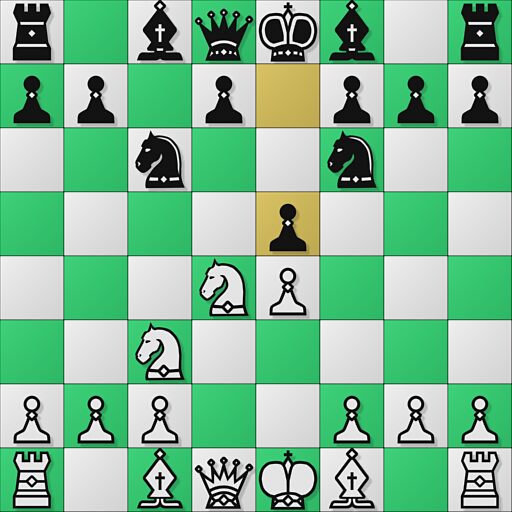
Chess 7 to darmowy font z szachowymi symbolami, utrzymany w prostym stylu gier planszowych. Symbole te wyglądają jak czytelne motywy szachowe, a nie ozdobne ikonki. Dzięki znanym sylwetkom figur i prostym geometrycznym kształtom zestaw jest bezpośredni i nie pozostawia wątpliwości co do swojej tematyki.
Świetnie sprawdzi się na ulotkach klubowych, plakatach turniejowych, kartach wyników, stronach z zadaniami oraz na opakowaniach gier – wszędzie tam, gdzie darmowy font z szachową grafiką sprawdzi się lepiej niż zwykły zbiór symboli. Użyj go do tytułów, krótkich wyróżnień, oznaczeń sekcji lub drobnych akcentów graficznych, gdy chcesz wprowadzić szachowy klimat bez wrażenia przesadnej ozdobności.
Chess-7
Style-7.ru
Created specially for game CHESS-7